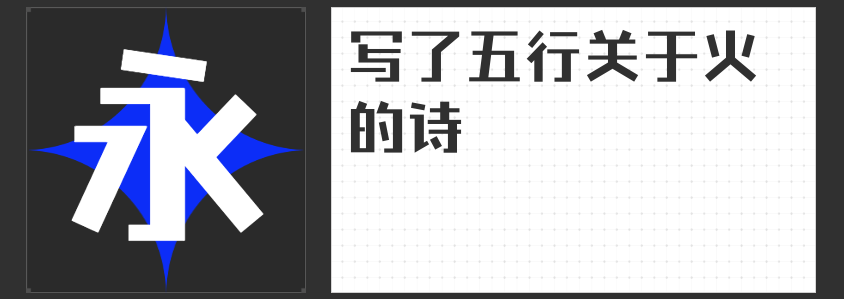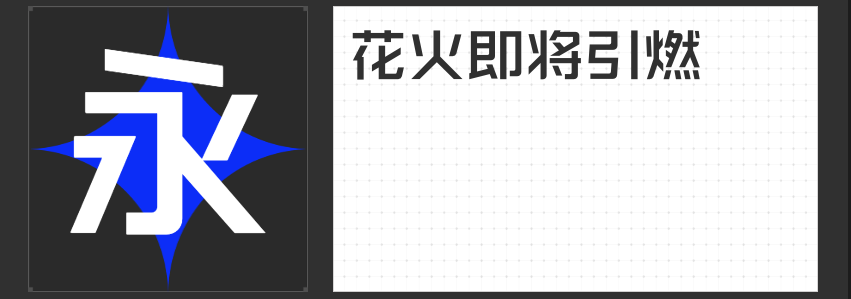
【字体推荐】为你的设计增添独特魅力——四款特色中文黑体介绍
在设计领域,字体的选择往往能够决定作品的第一印象。尤其是黑体,因其简洁明快、辨识度高的特性,被广泛应用于各种场合。今天,我们就来介绍四款独具特色的中文黑体。无论你是设计师还是品牌策划人员,这些字体都将为你的项目带来不一样的视觉体验。
1.励字钧线黑简 大黑
“励字钧线黑简 大黑”以其均衡的线条和大胆的笔画脱颖而出。这款字体采用特大号的粗度设计,给人以强烈的视觉冲击力。其笔画粗犷而有力,非常适合用于强调文字信息,比如海报标题或重要标语。如果你的设计需要传达一种坚定、有力的信息,“励字钧线黑简 大黑”将是不二之选。
2.励字勇敢黑简 中黑
“励字勇敢黑简 中黑”在保持了黑体基本特征的同时,加入了一些细腻的变化,使其更具个性。它的笔画相比“大黑”更为适中,既有力度也不失柔和。这种字体非常适合用于需要平衡力道与美感的设计项目,如产品包装、广告宣传或是网站标题等。它既能突出主题,又能保证整体设计的和谐统一。
3.励字开拓者简 超黑
“励字开拓者简 超黑”以其超粗的笔画和强烈的对比度成为一款非常引人注目的字体。它的设计灵感来源于开拓者的勇气和决心,适用于那些需要彰显力量感和突破精神的场合。无论是用于品牌形象设计还是活动宣传,“励字开拓者简 超黑”都能够帮助你的作品在众多设计中脱颖而出,给受众留下深刻印象。
4.励字志向黑简 大粗
最后介绍的“励字志向黑简 大粗”是一款充满激情与梦想的字体。它以大粗的笔画为基础,展现出一种积极向上的态度。这款字体非常适合用于表达个人或品牌的雄心壮志,能够在视觉上传达出强烈的情感和动力。无论是用于励志书籍的封面设计还是激励人心的口号标语,“励字志向黑简 大粗”都能够完美地匹配这一主题。
总结来说,这四款特色中文黑体各有千秋,不仅在视觉效果上能够给设计带来新鲜感,还能根据不同的设计需求,为作品注入特定的情感和氛围。希望今天的推荐能够为设计师们提供更多灵感和选择,让你的作品更加出色!